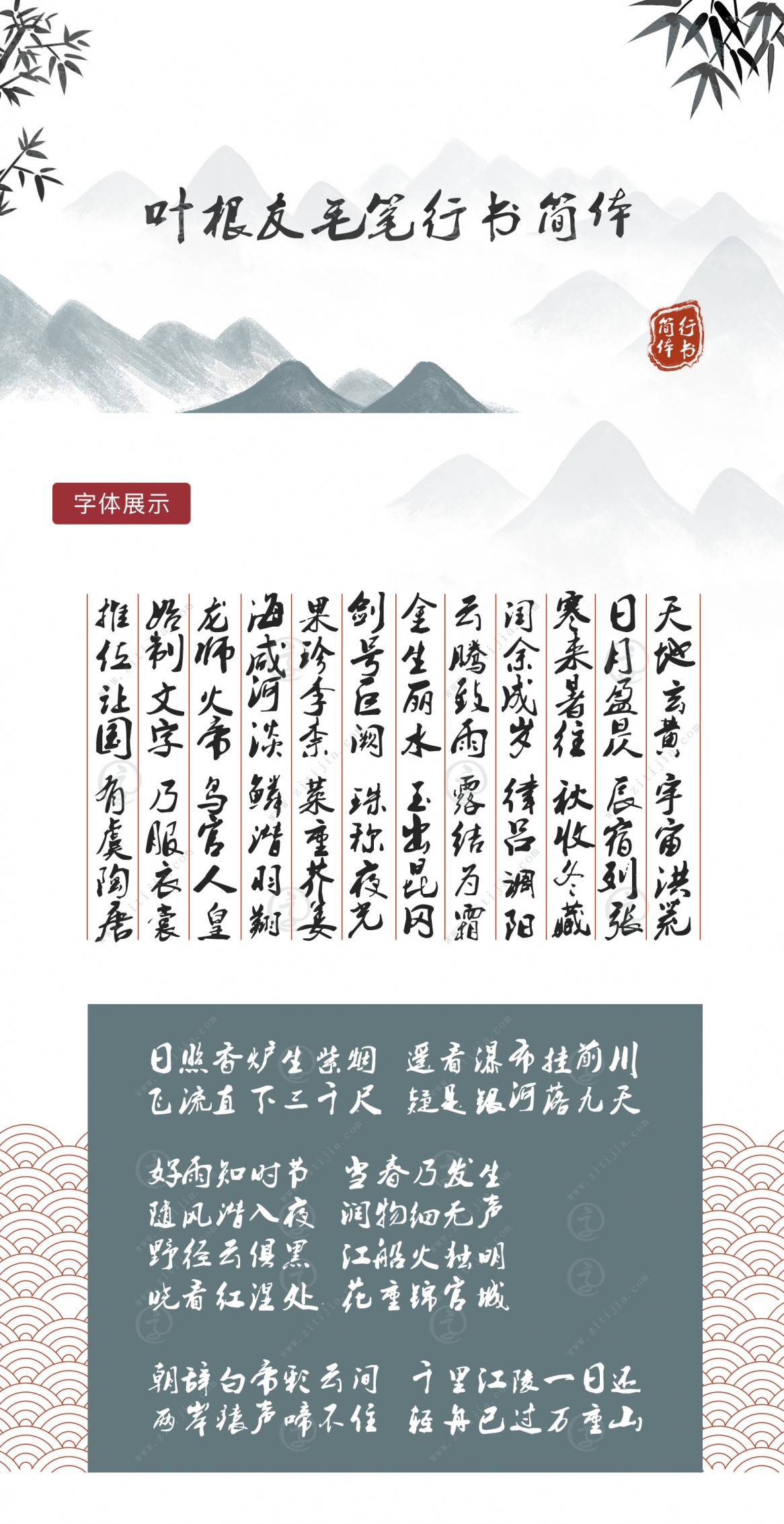
葉根友毛筆行書簡體2.1
字體作者:葉根友
創(chuàng)作年代:2007年
字體字?jǐn)?shù):6763個(gè)中文漢字以及其他英文字母和阿拉伯?dāng)?shù)字
字體介紹
這是一款葉根友字體系列最受歡迎的字體之一,葉根友毛筆行書簡體是具有獨(dú)特風(fēng)格的字體,筆意取自米芾書法風(fēng)格,大氣而又自然流暢是這款字體的主要風(fēng)格。廣泛應(yīng)用于社會(huì)各界的廣告招牌、影視作品以及游戲應(yīng)用等。
一款2007年創(chuàng)意的字體,筆畫風(fēng)格大氣流暢,書寫自然,是一種純手寫字體的經(jīng)典之作,之前第一版顯示葉根友毛筆行簡體“明”字錯(cuò)誤,在2011年時(shí)已經(jīng)更正該錯(cuò)誤,請各用戶注意甄別,如善未替換的用戶請重新下載該升級版葉根友毛筆行書字體,2010年2月4日升級完成該版本2.1版本升級,重新書寫了英文26個(gè)大小寫字母和數(shù)字以及漢字的筆畫信息優(yōu)化,調(diào)整了字?jǐn)?shù)上下距離、大小等。
創(chuàng)作記事
2007年8月,初創(chuàng)該字體字稿
2007年11月,發(fā)行葉根友毛筆行書1.0版本
2010年2月,重新調(diào)整該字體中字與字的比例、大小位置等更新升級
2020年5月,重新調(diào)整部分字型以及修正蘋果電腦系統(tǒng)不兼容問題